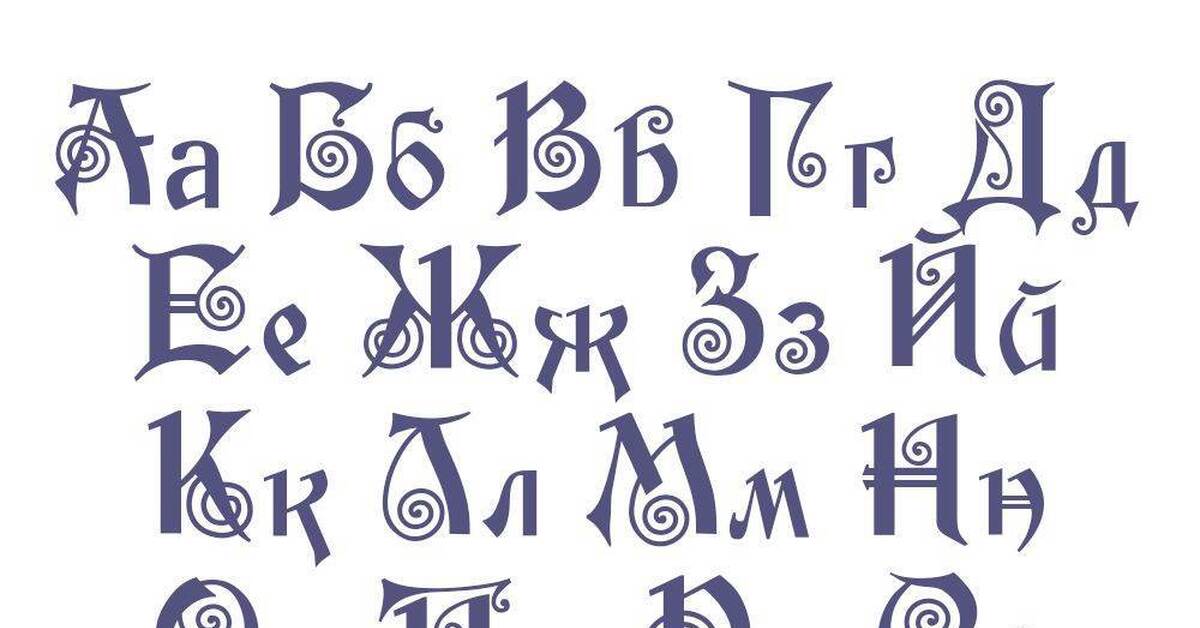
Красивый шрифт для текста онлайн на русском, каталог для Инстаграма, скопировать для ника
Шрифты – это инструмент, который помогает сделать сайт или социальную сеть более запоминающейся.
С помощью красивых заголовков или надписей можно подчеркнуть значащую часть поста, оформить ник в Instagram и заинтересовать аудиторию. Статья, исполненная в необычном стиле, сразу привлекает внимание.
Сначала выберите шрифт. На странице сервиса представлен каталог с вариантами написания текста с примерами, от обычных декоративных рукописных шрифтов до эмоджи или изображений. Когда выбираете оформление, ориентируйтесь на содержание вашей статьи и общую стилистику сайта. Предложения должны не только красиво выглядеть, но и раскрывать смысл поста.